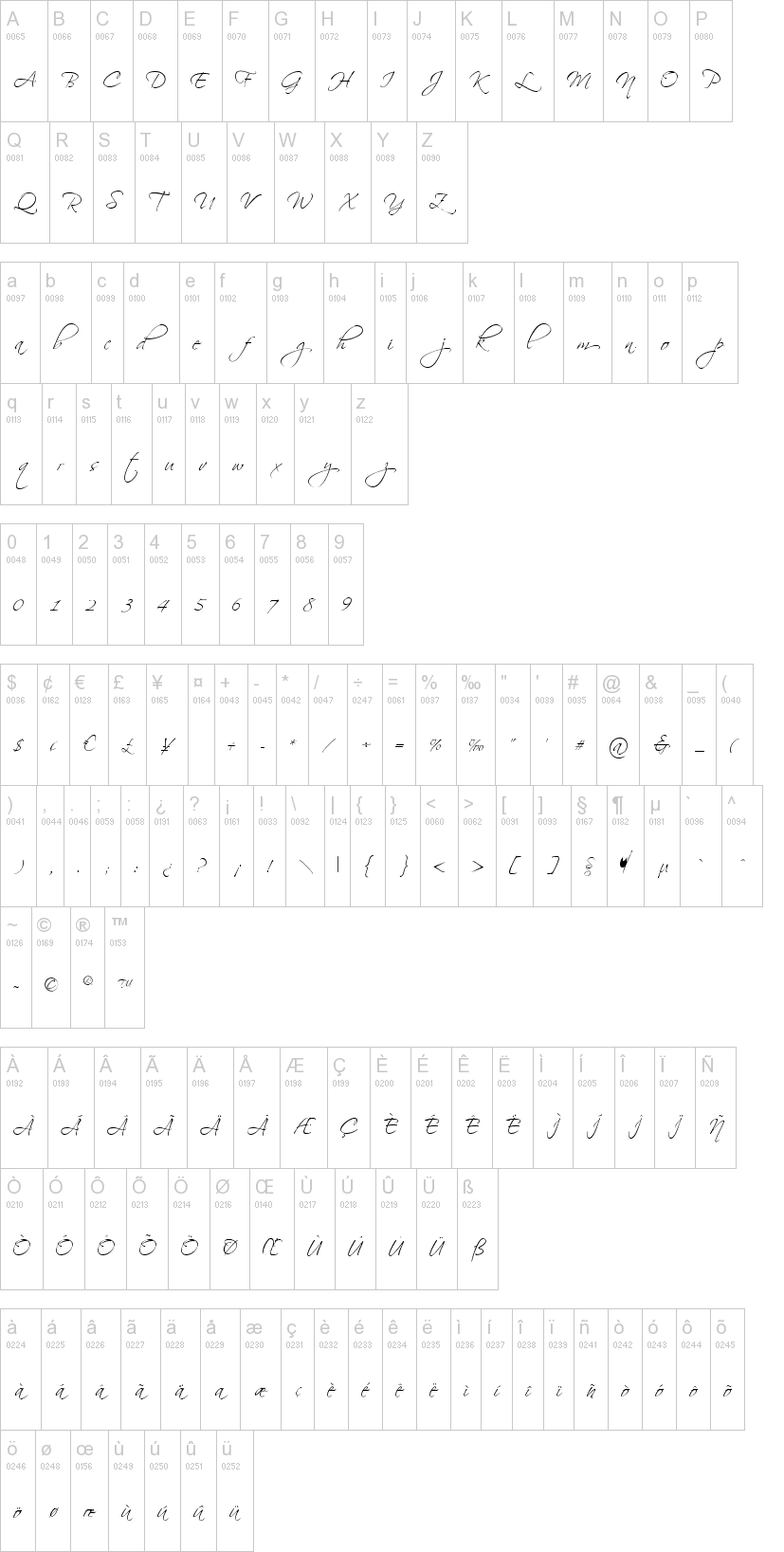
Scriptina
Scriptina 是一款由 Astigmatic One Eye Typographic Institute 创作的免费字体,它是一款非常流行的手写字体,具有流畅的线条和温柔的笔画,能够为文本提供极佳的可读性。它的设计灵感来自于古典的手写体,具有舒适的节奏和温暖的气氛,适合用于网站的标题和段落文本。
Scriptina是一款非常不错的手写艺术字体,具有很好的视觉感,适合于文化类的宣传设计、商业类品牌的广告和产品包装设计以及个性化文字排版等较多场景。
Scriptina字符映射图